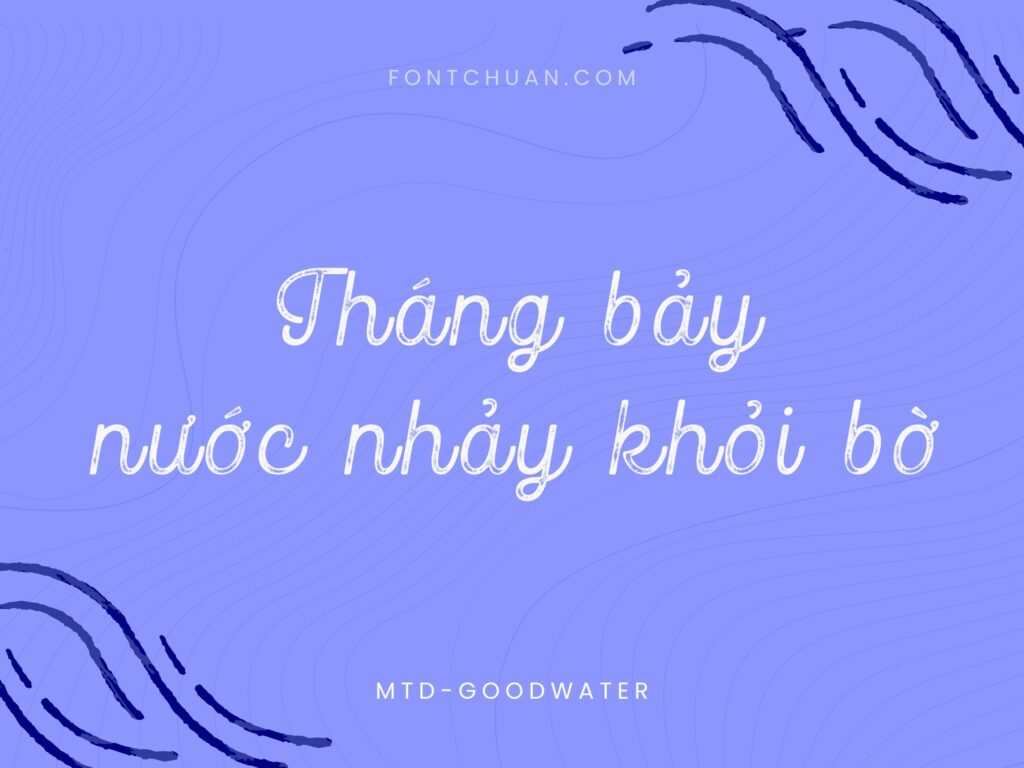
Font MTD Goodwater Việt Hóa
Font MTD Goodwater Script là một kiểu chữ viết tay mềm mại và uyển chuyển, mang đến cảm giác thân thiện và gần gũi. Được Việt hóa bởi Mộc Hạ, font này hỗ trợ đầy đủ tiếng Việt cùng hơn 90 ngôn ngữ khác, mở rộng khả năng ứng dụng trong các thiết kế đa ngôn ngữ. Đây là một trong những phông chữ được cộng đồng thiết kế đánh giá cao và sử dụng trong nhiều dự án sáng tạo, đáp ứng nhu cầu đa dạng của người dùng.
MTD Goodwater Script nổi bật với các đường nét tự nhiên và thanh lịch, rất phù hợp cho các thiết kế logo, tiêu đề, bao bì sản phẩm, thiệp mời và các ấn phẩm đòi hỏi sự sáng tạo và cá nhân hóa. Các ngành nghề phù hợp bao gồm quảng cáo, giáo dục, công nghệ, thiệp cưới và ảnh cưới. Font này cũng lý tưởng cho các sự kiện như Tết, Giáng sinh, Valentine và các lễ hội khác.